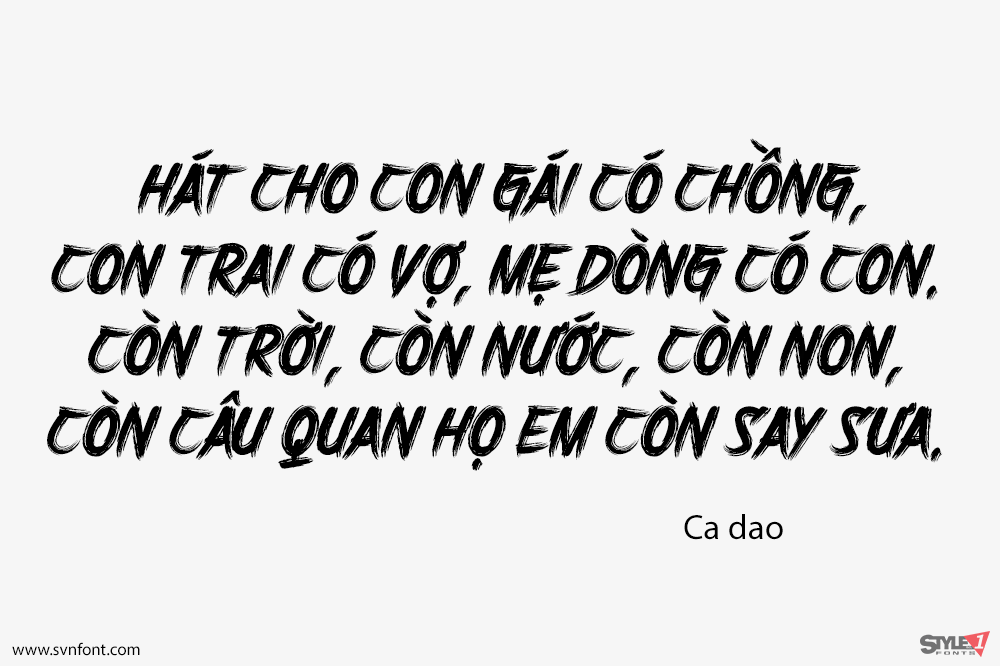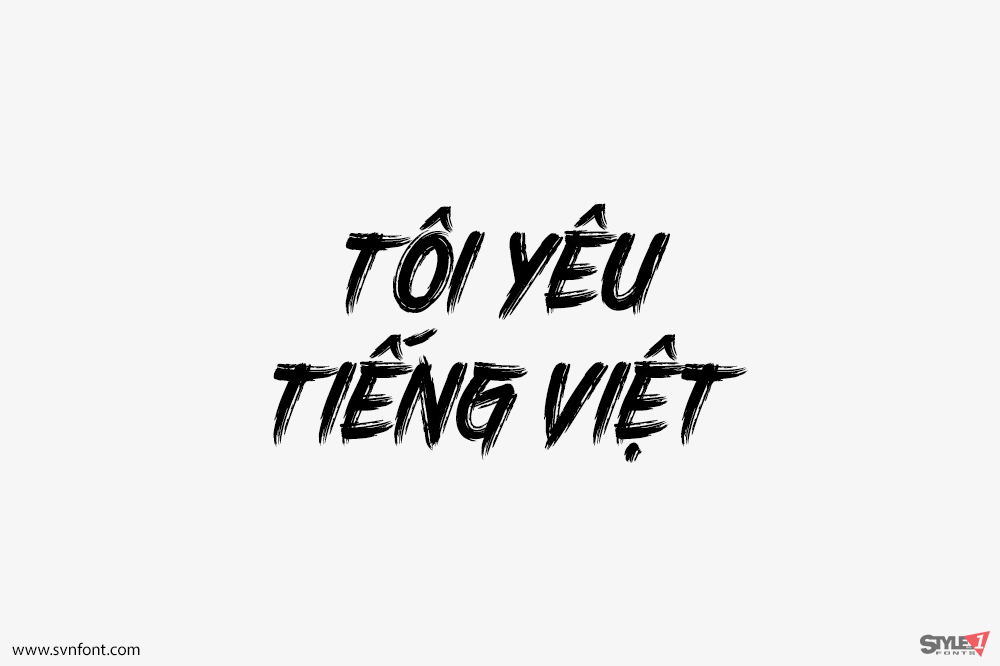
Harry’s Brush là một font chữ viết tay dạng cọ vẽ, được thiết kế bởi Dexsar Harry Anugrah. Mỗi chữ cái được vẽ lại một cách đầy tỉ mỉ, giữ đúng chất của một font cọ vẽ. Font thích hợp cho các thiết kế cần sự phá cách, tự nhiên, phóng khoáng và nghệ thuật như: logo thương hiệu, poster, banner, tiêu đề (headline), bìa sách, menu nhà hàng, bao bì sản phẩm, thời trang,…
Nhà thiết kế: Dexsar Harry Anugrah
Nhà phát hành: Dexsar Harry Anugrah